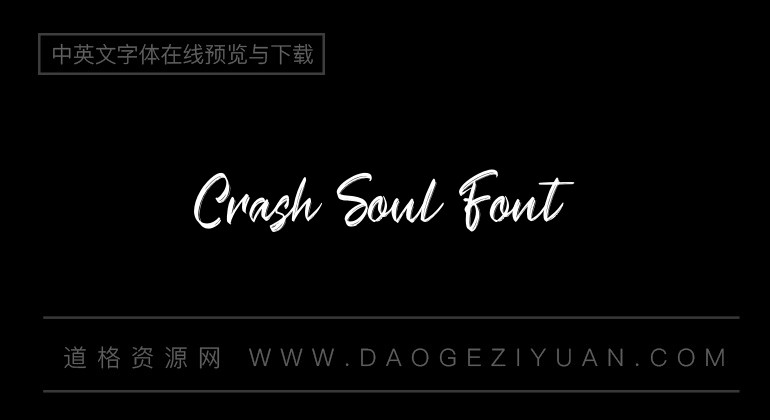
Crash Soul Font是一种免费的手写字体,具有黑体和草书的复古风格。该字体具有粗犷、有力的特点,适用于标题、海报、标志等设计用途。 Crash Soul Font字体的字形较为简单,但具有浓郁的艺术气息,配合颜色和图形使用可以营造出非常独特的视觉效果。该字体支持英文字母、数字、标点符号和一些特殊字符,可用于设计不同风格的文本内容。 总的来说,Crash Soul Font是一种适用范围较广的字体,尤其适用于那些需要突出复古、手写风格的设计项目。内容介绍
Crash Soul Font是一款非常不错的手写艺术字体,具有很好的视觉感,适合于文化类的宣传设计、商业类品牌的广告和产品包装设计以及个性化文字排版等较多场景。